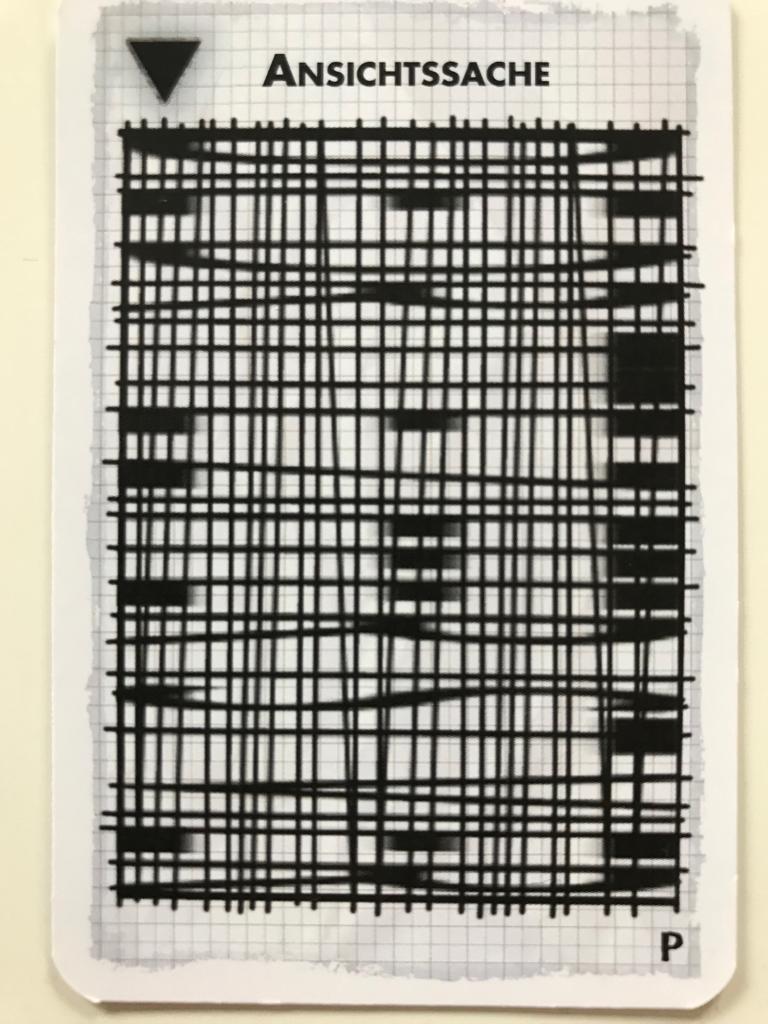
"Geheimschrift" aus Kosmos "Das geheime Labor"
hat jemand einen Tipp, wie ich diese Geheimschrift nachmachen kann? Gibt es dafür einen Font? (Man kann sie besonders gut lesen, wenn man von der Seite schräg darauf guckt; dann kann man lesen "DIE DRITTE ZIFFER IST VIER").
Ich glaube nicht, dass es dafür einen Font gibt. Ich würde empfehlen, so eine Grafik in einem Vektorprogramm zu erstellen, z.B. InkScape oder Illustrator. Erst in der Endgröße die horizontalen Linien ziehen, dann alles vertikal herunterskalieren, die Lösung einbauen und wieder vertikal hochskalieren.
Übrigens gibt es diese Art von Rätsel auch mit zwei Lösungen, die man aus zwei verschiedenen Blickrichtungen erkennen kann.